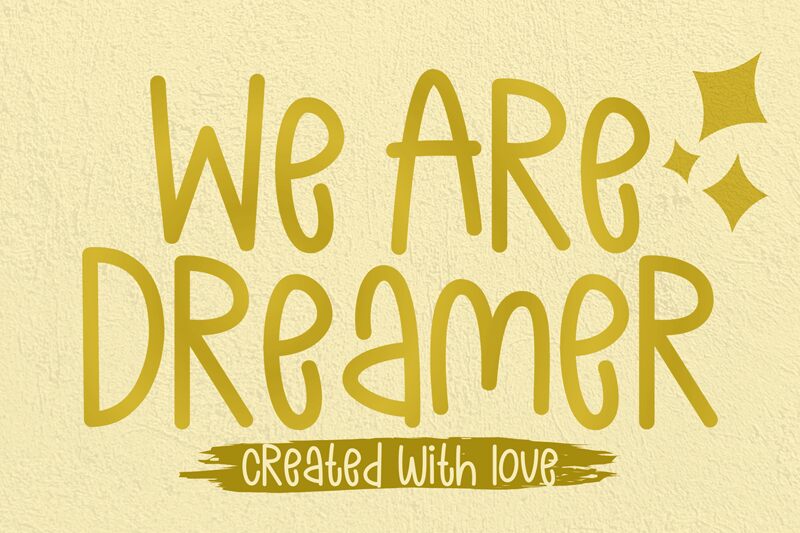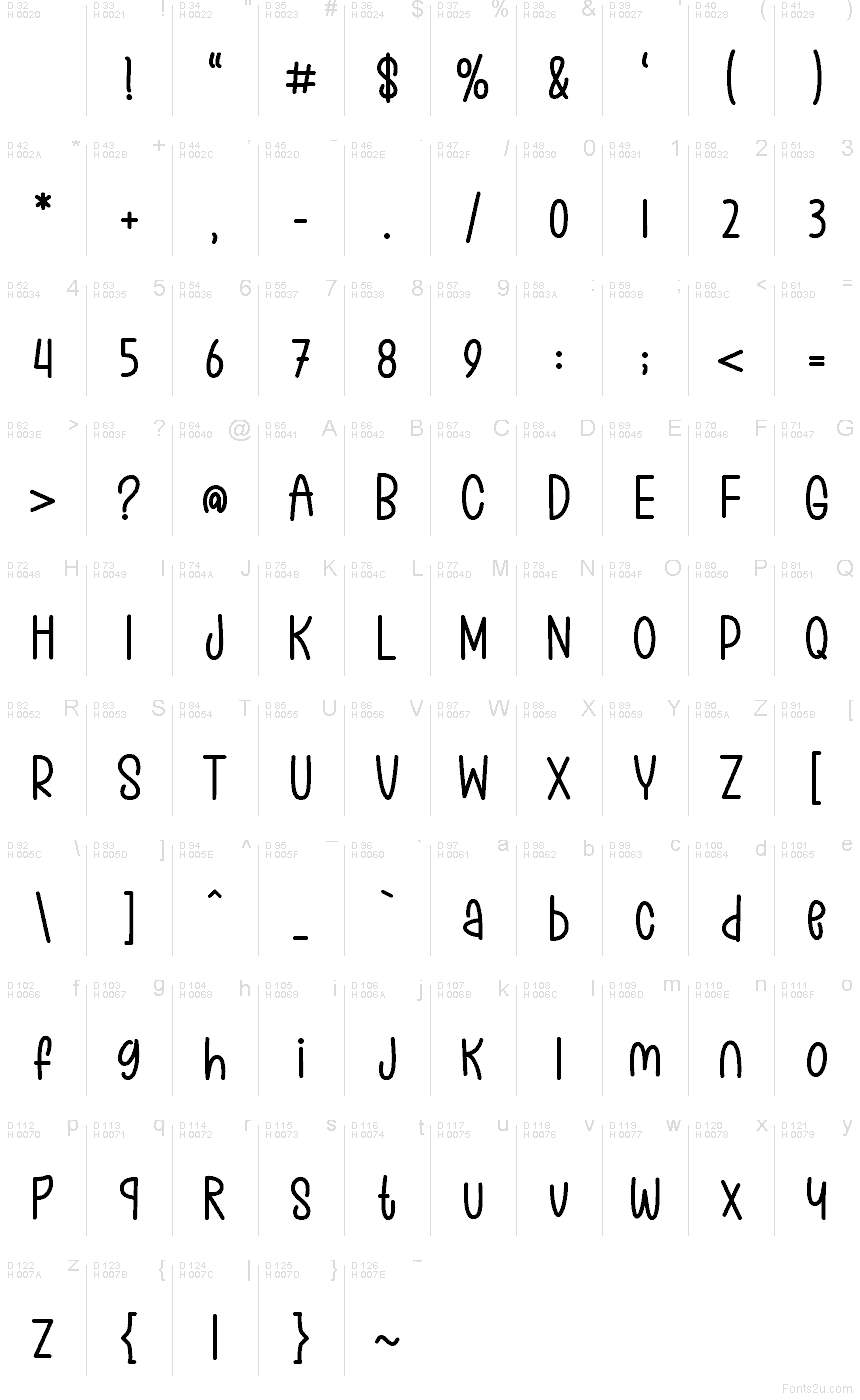
We Are Dreamer od Mabhal Studio to darmowy, odręczny krój pisma typu display, o luźnym, markerowym rytmie. Litery są wysokie, dynamiczne i lekko nierówne, a zaokrąglone kształty oraz domowy charakter sprawiają, że styl jest żywy, a nie przesadnie uporządkowany.
Świetnie sprawdza się na plakatach, w brandingu kawiarni, na okładkach zeszytów, opakowaniach dla dzieci czy w tytułach w mediach społecznościowych, gdzie ludzki pierwiastek liczy się bardziej niż ścisła geometria. Jako darmowy font, doskonale nadaje się również do krótkich nagłówków, zabawnych logo i szybkich grafik kampanijnych, ponieważ delikatna nieregularność liter nadaje nawet prostym słowom swobodnego wyrazu.
Prezentacja i próbka wizualna czcionki We Are Dreamer
Mapa znaków czcionki We Are Dreamer
Mapa znaków czcionki We Are Dreamer: Podstawowy łaciński, strona 1
Glify czcionki We Are Dreamer — Podstawowy łaciński, strona 1